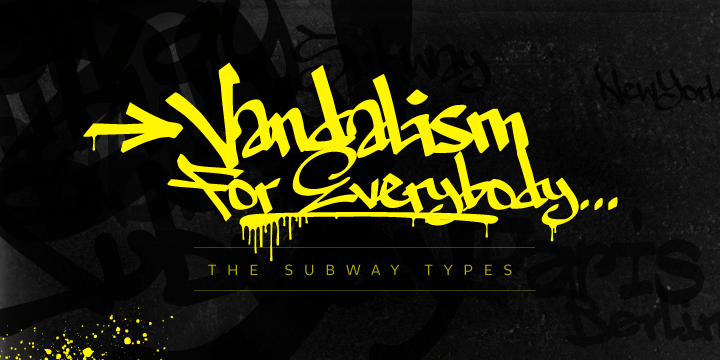
The Subway Types Font Family – Download Grátis
A fonte “The Subway Types” é uma criação única e detalhada criada pelo designer Hamilton. Ela está equipada para atender às necessidades mais exigentes, com cada tipo incluindo quatro alfabets (maiúsculas, minúsculas grandes e assinaturas). Além disso, também oferece ligaduras e alguns especiais como soblinhados e uma vasta gama de acentos para suportar um grande número de idiomas. Sua natureza sofisticada e detalhada torna-a perfeita para designers gráficos exigentes que buscam um acabamento elegante em suas criações. A “The Subway Types” é ideal tanto para designers de nomes quanto para a criação de logotipos ou materiais de marketing onde uma aparência clássica e sofisticada são necessários. Ela oferece todos os recursos que você precisa para manter seu design atualizado e respeitável, enquanto mantendo um toque único e marcante.